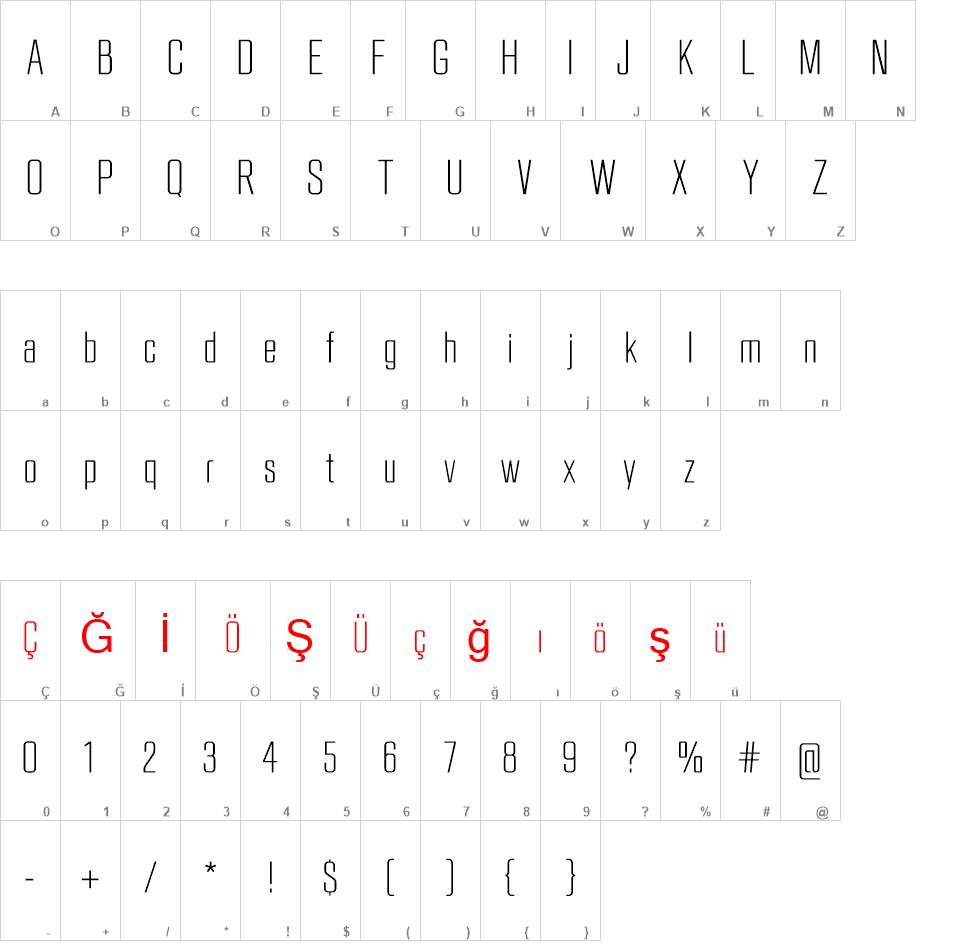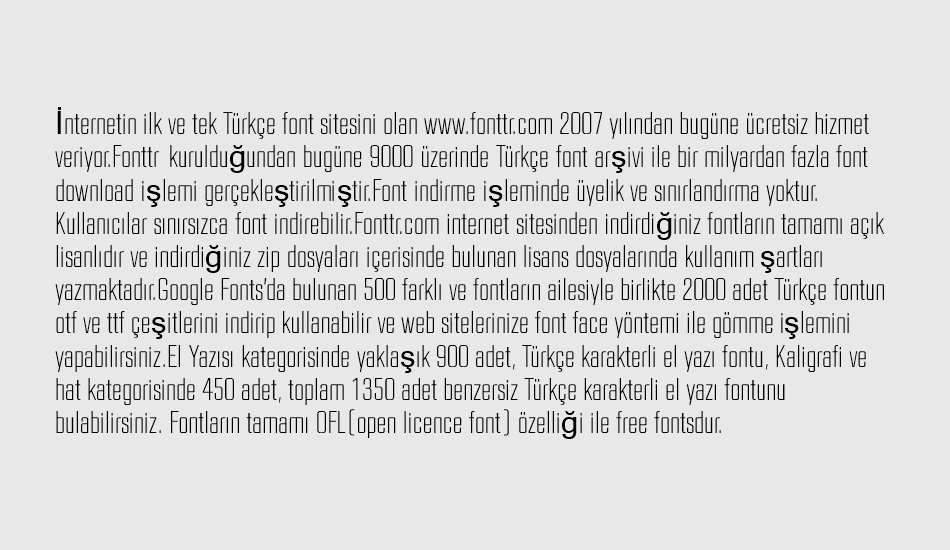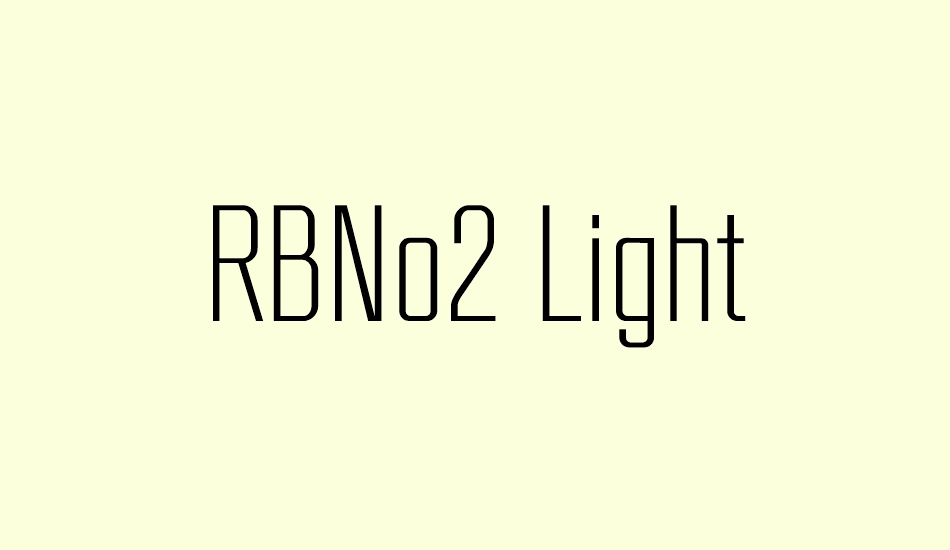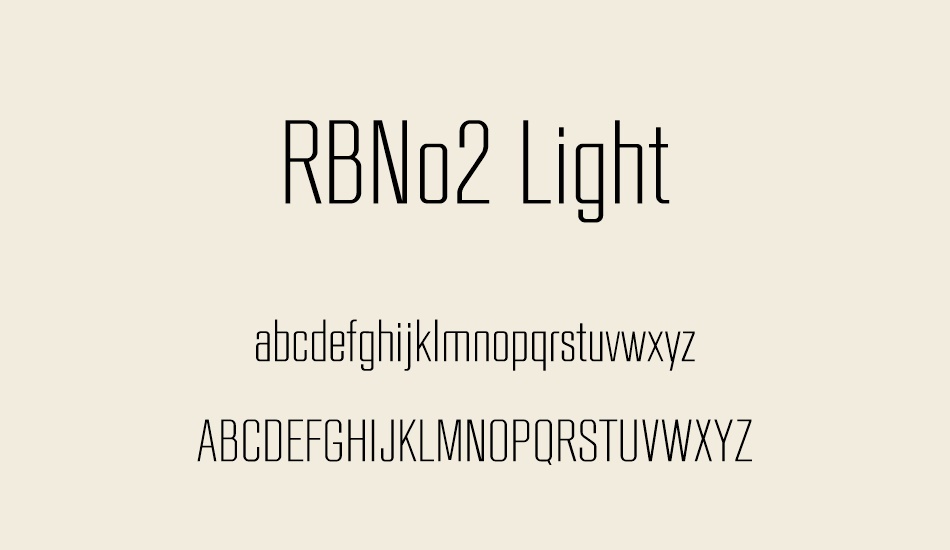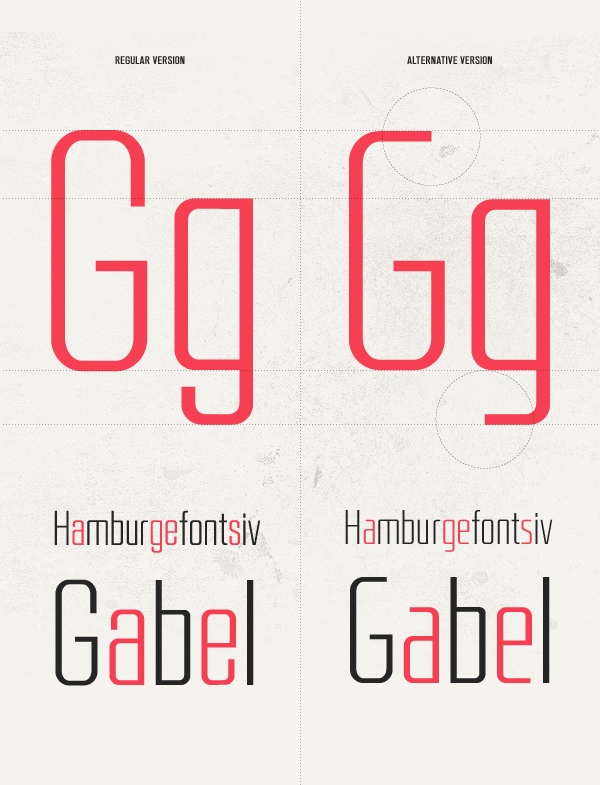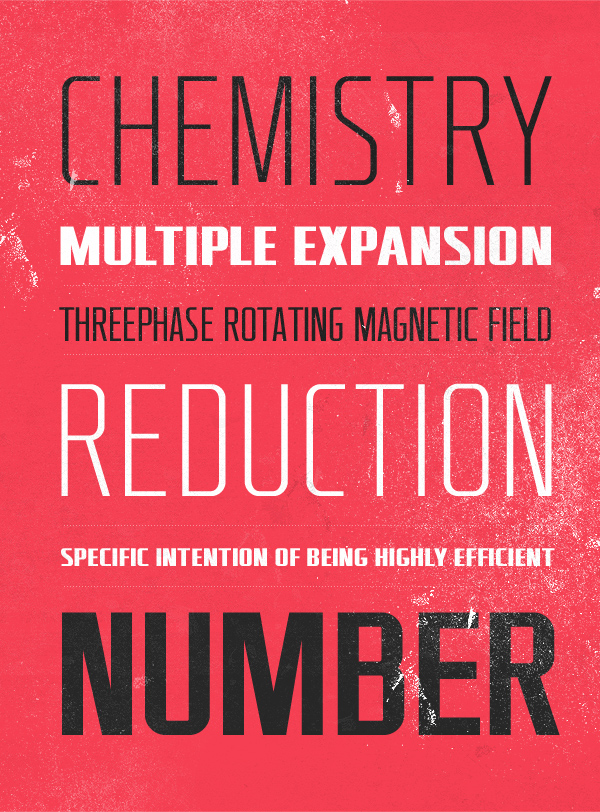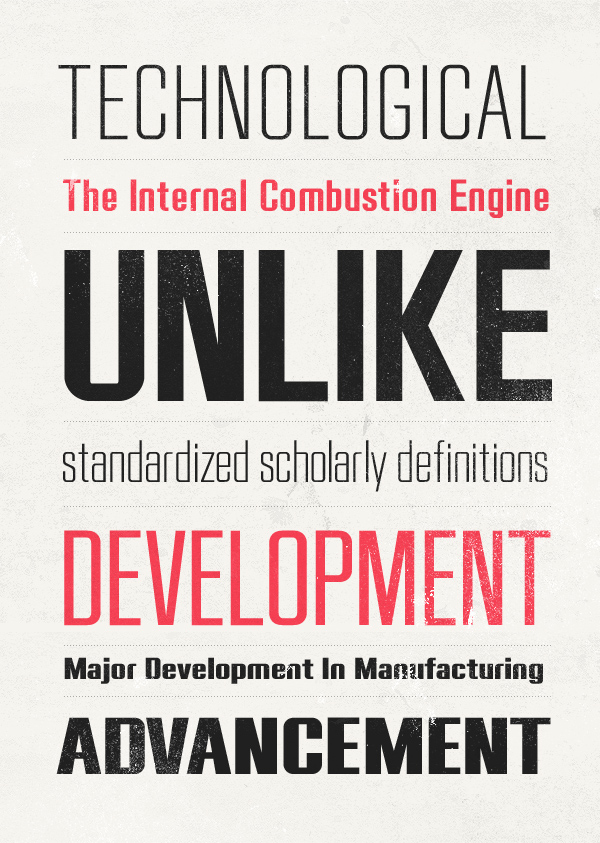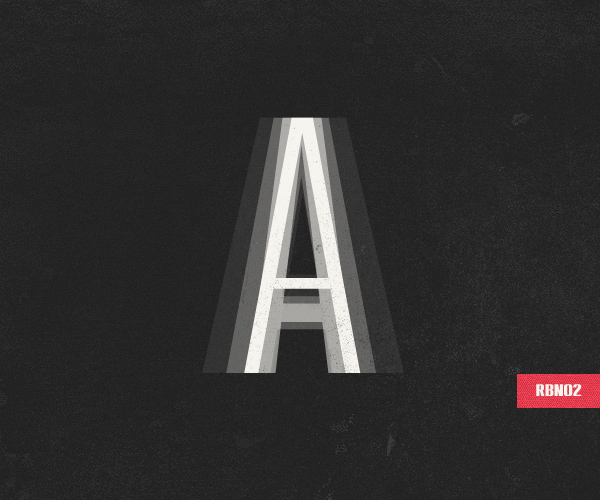
RBNo2 font
Düzgünlük ve geometri ile ilgili Alman kökenli 19. yüzyılın sonlarından kalma endüstriyel yazı tiplerinden esinlenilmiştir. Diğer sans serifleri, kütük serifleri ve serif yazı tipleri ile birleşince, manşetlerde ve kısa metnin metinlerinde göze çarpar. Normal stillere ek olarak, alternatif sürümler yazı tipini, çağdaş, teknik ve çağdaş izlenimler için, ayrıca yüksek kaliteli, lüks ve zamansız ortamlar için mükemmel bir ortak haline getirecektir.
RBNo2 Light font